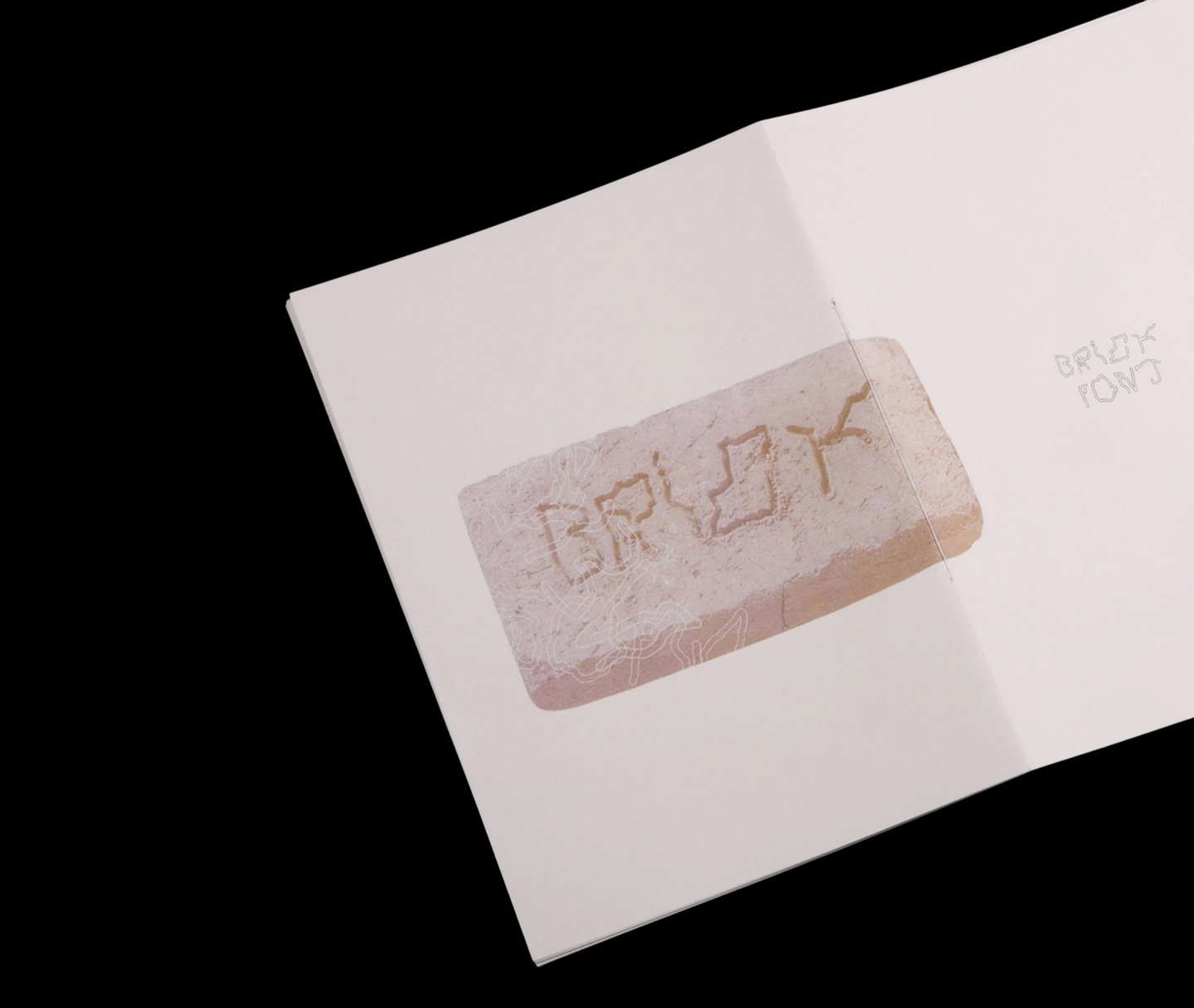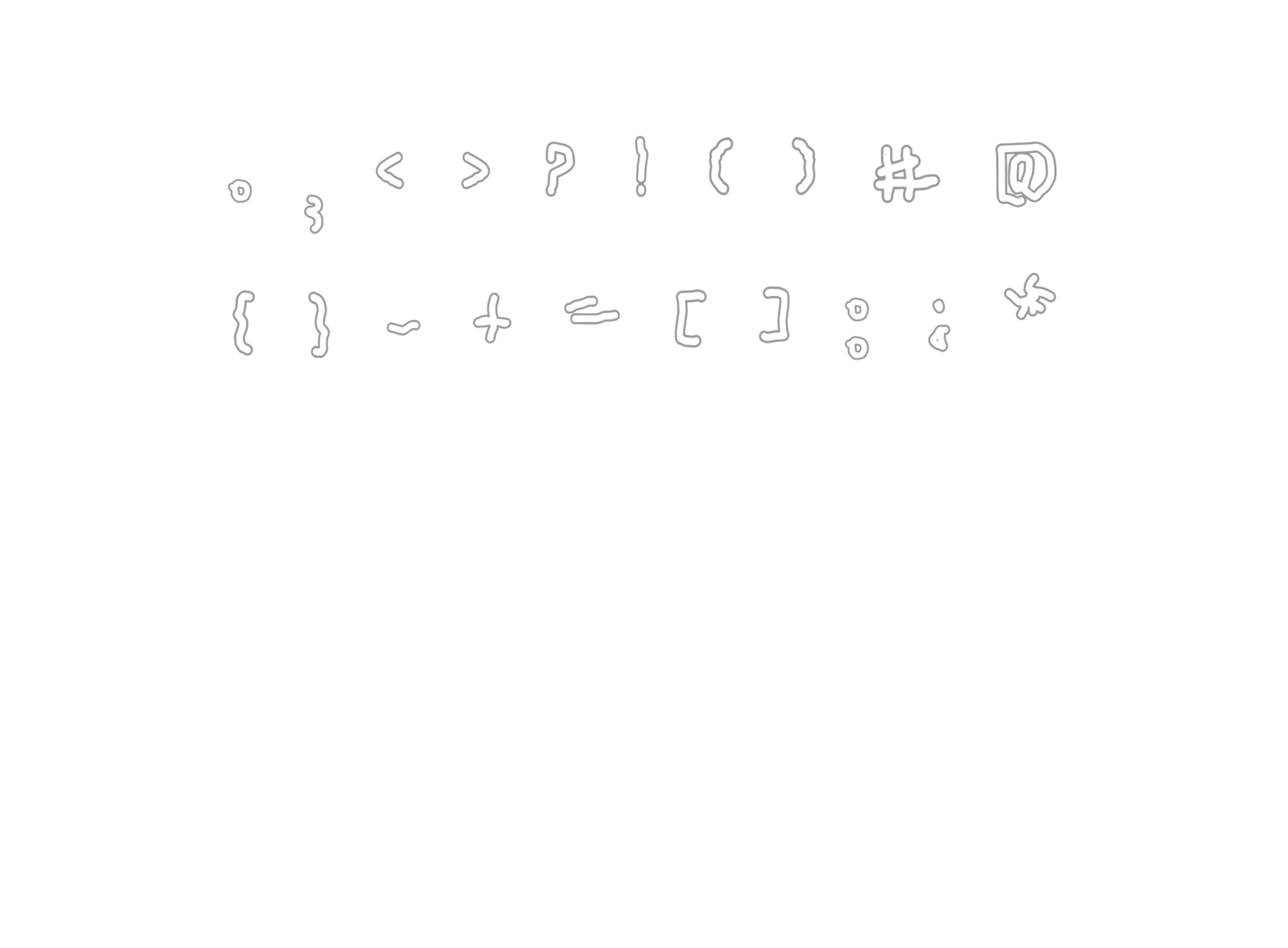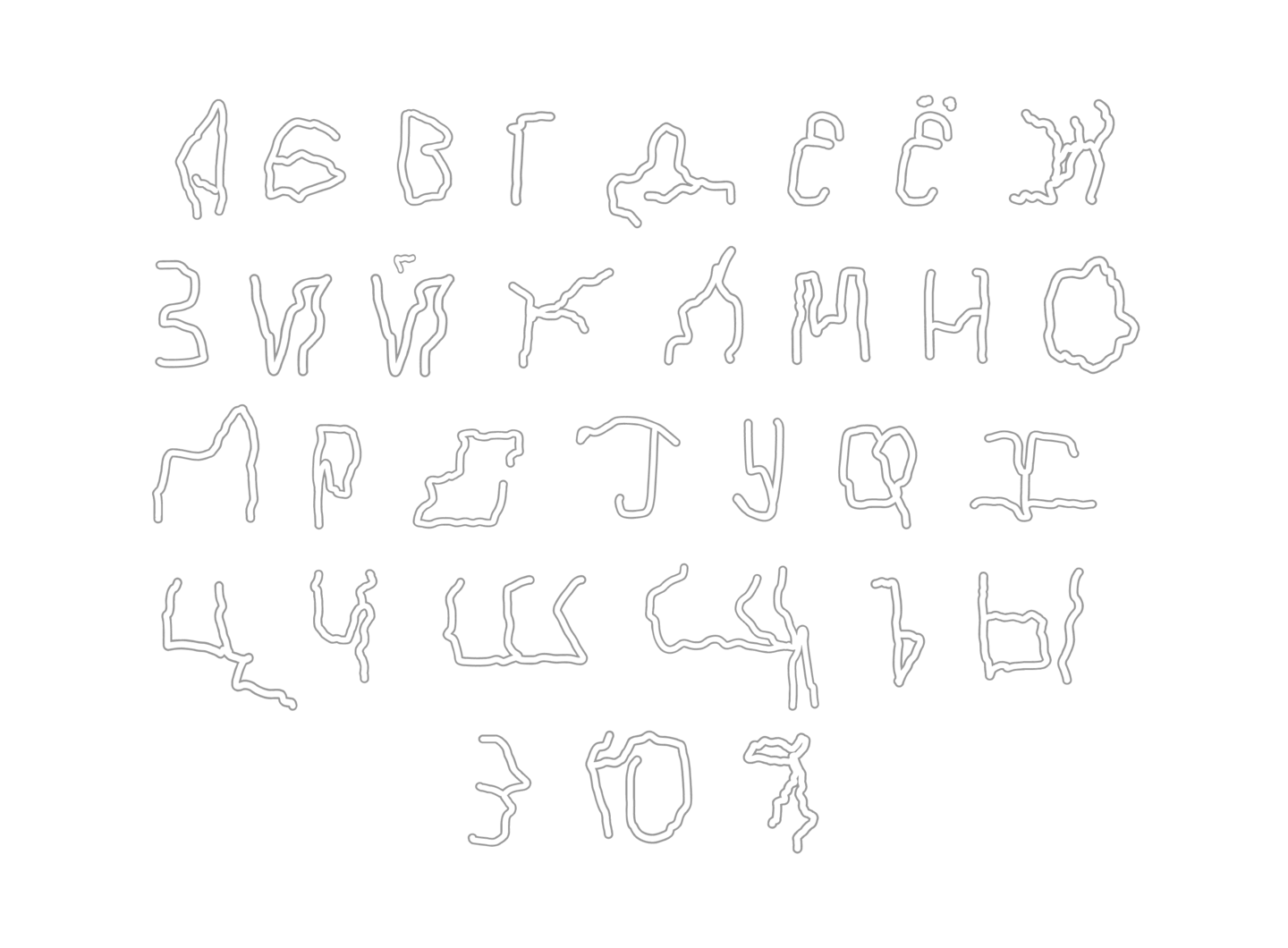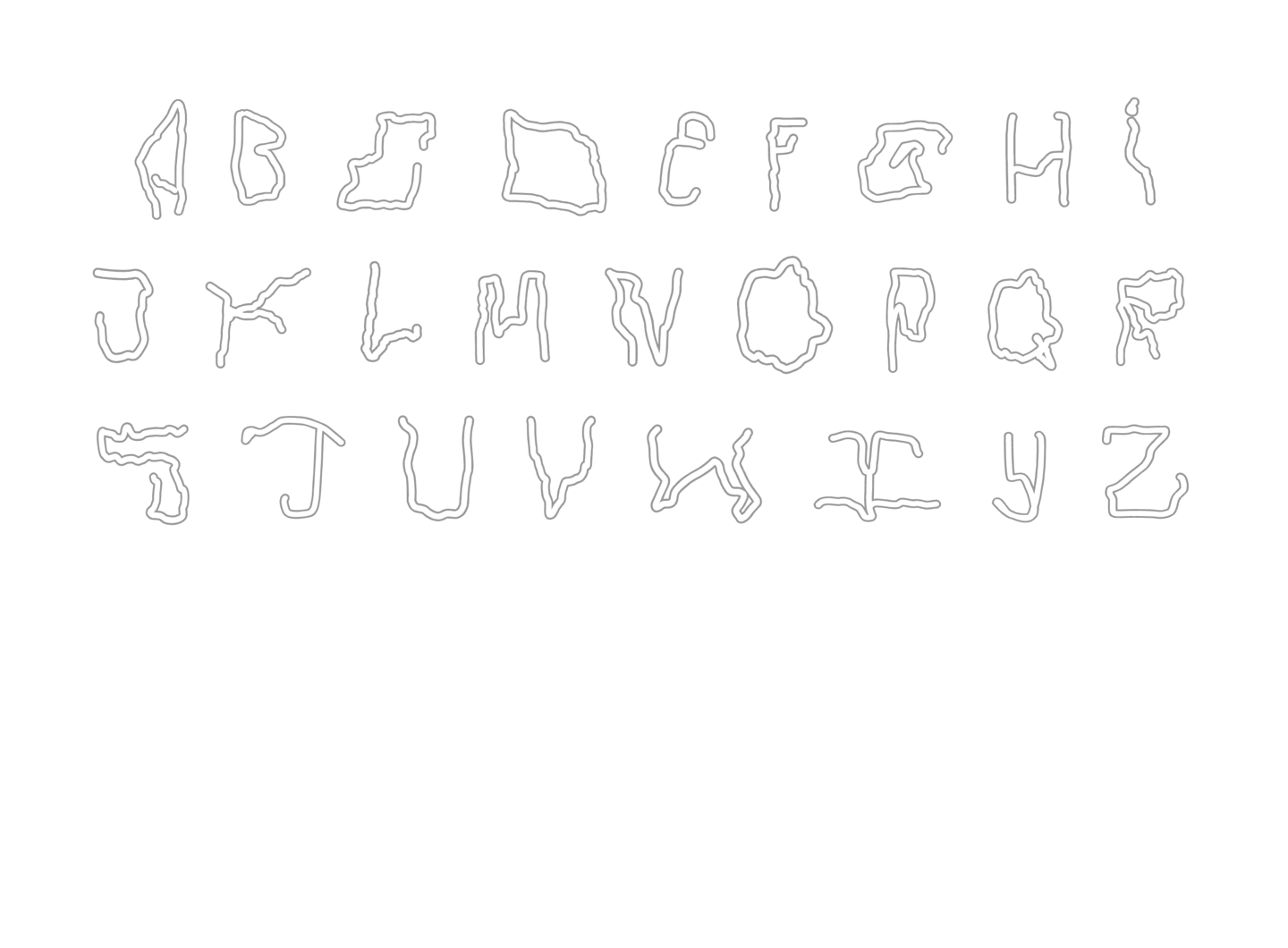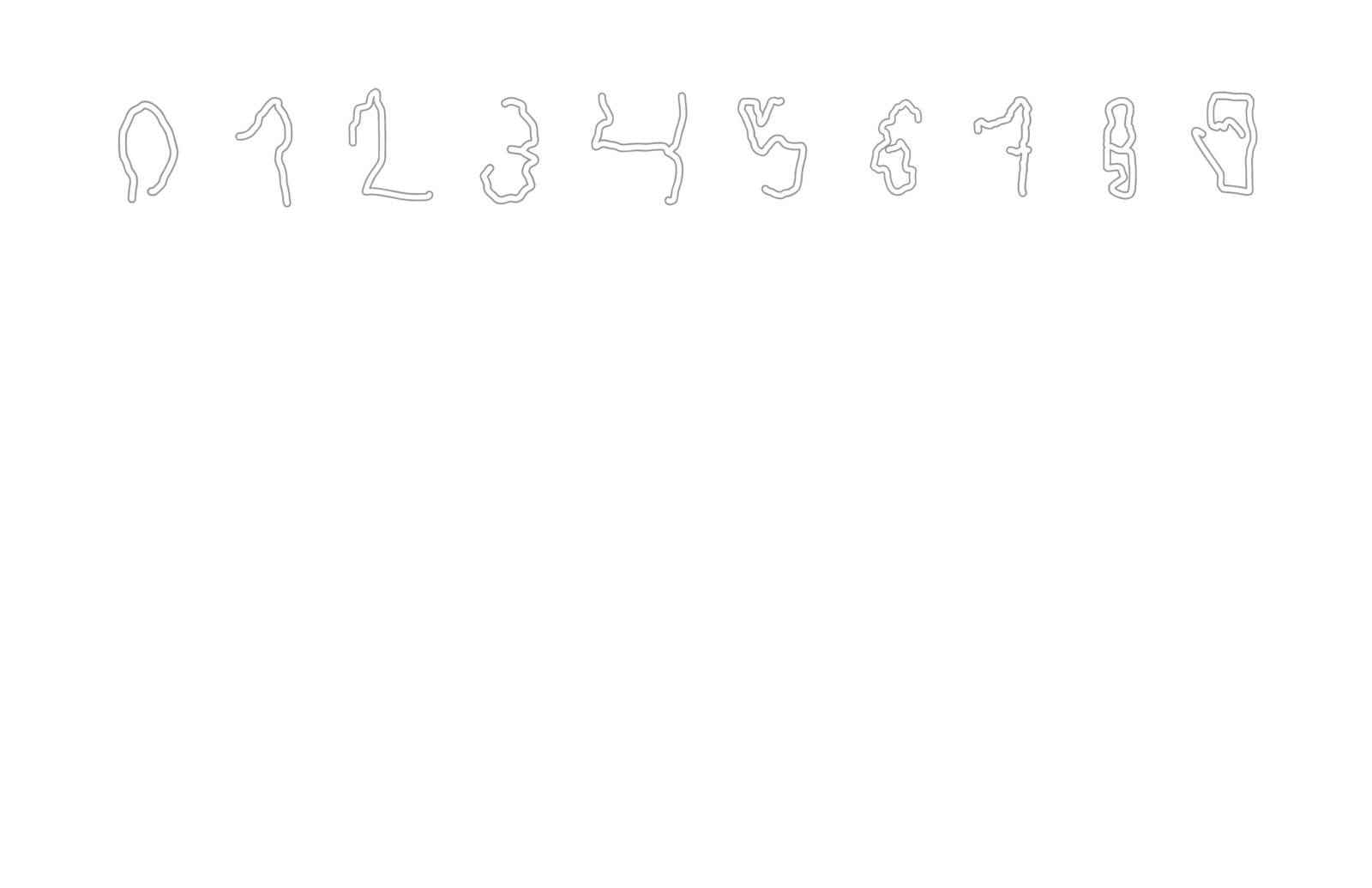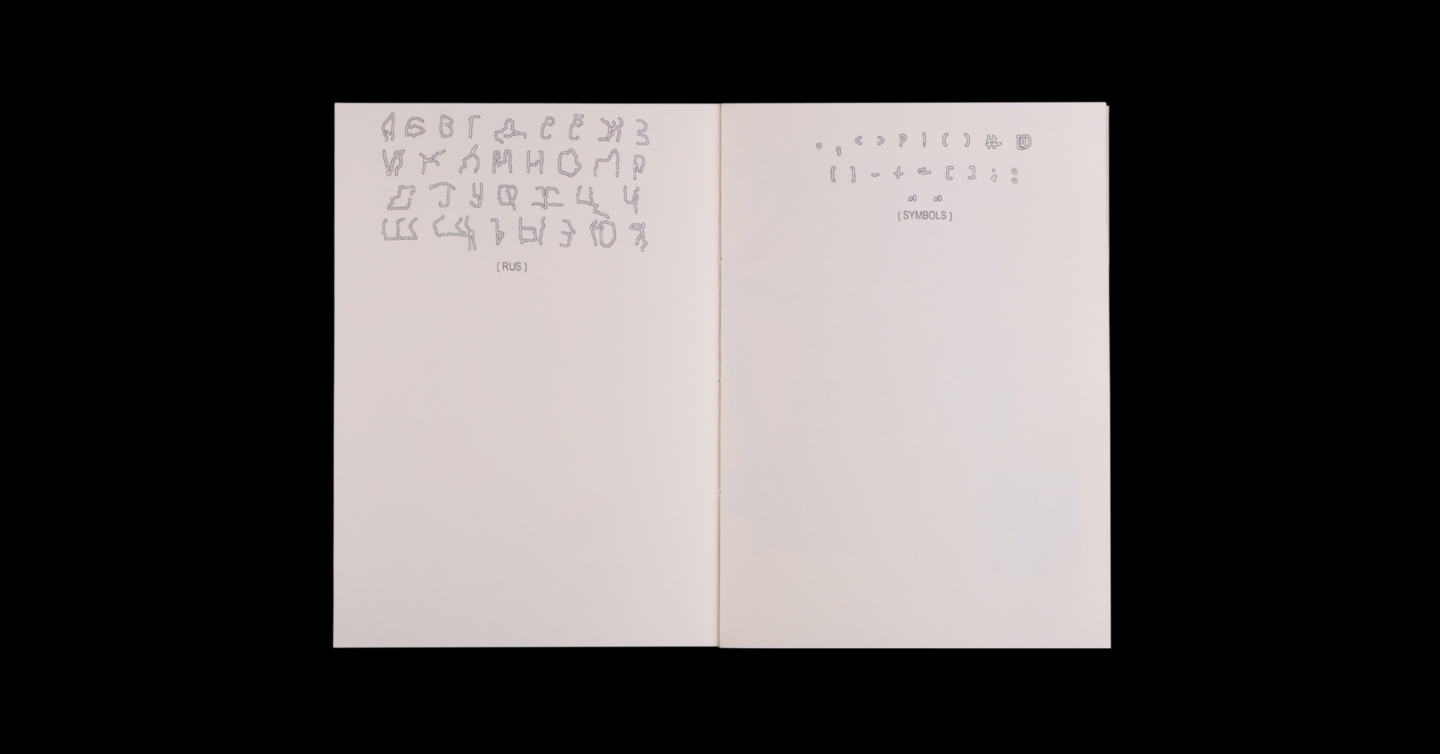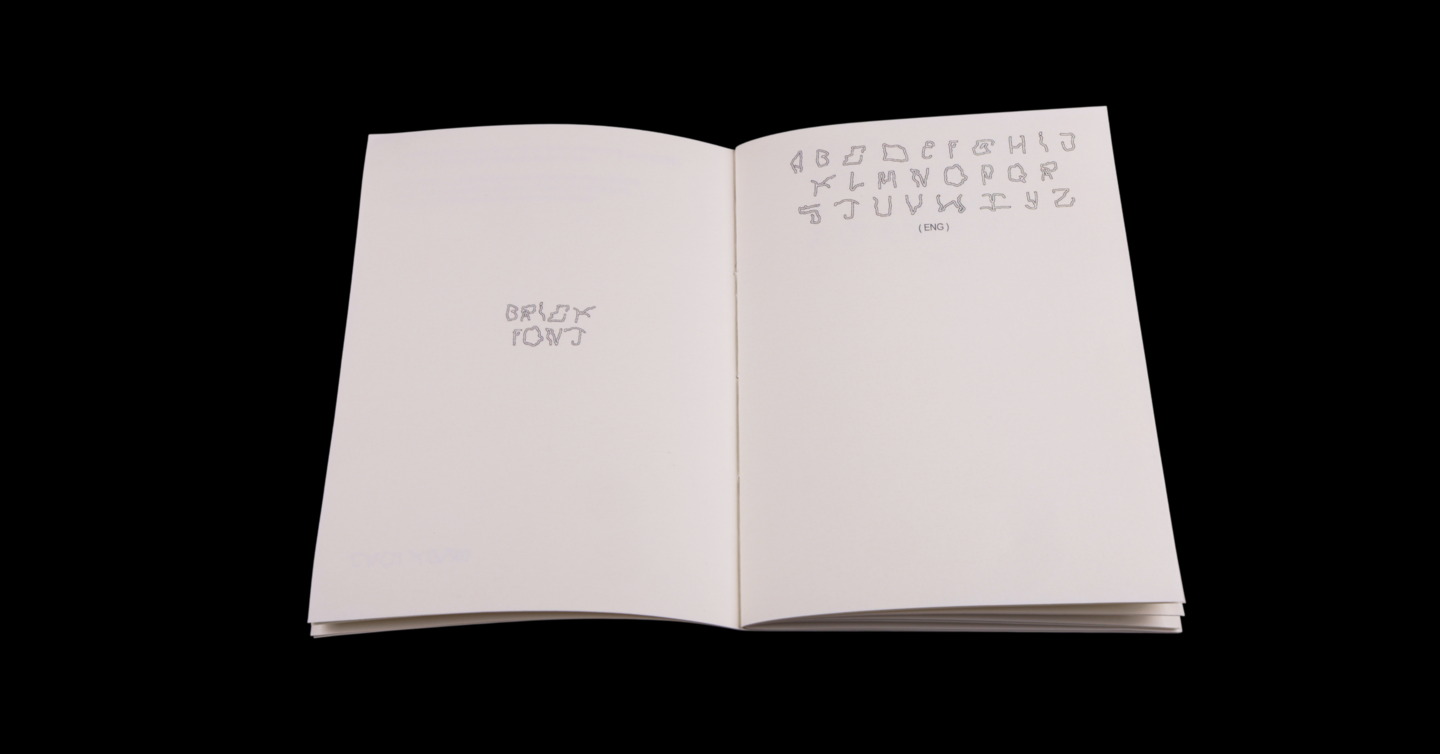
Brick. font
— шрифт, созданный из прожилок кирпичной стены, которая каждый день поддается давлению природы и искажается, ломается, обавливается, получает новую форму
касса
Шрифт вышел живым и свободным. Это то к чему я стремилась
поза буквы « К »
Та самая кирпичная стена
Калька сверху показывает фрагменты стены, в которых были найдены модули и буквы